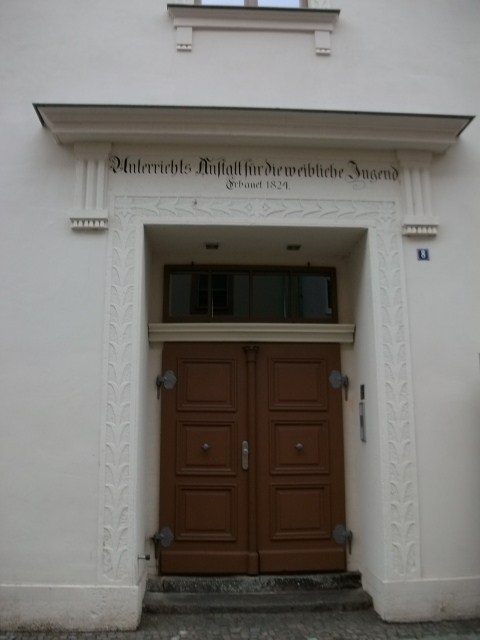
Vielleicht doch kein Faible der Engländer,
das Ungern-Koppeln bzw. -zusammenschreiben, Schnitzel?
Ehemalige Wittenberger Schulstätte.
Doch, hier ist es eben falsch ;-)
Aber in irgendeinem Thread wurde sich hier mehr oder weniger geeinigt, dass Eigennamen nicht unbedingt gekoppelt werden und sich nicht der gängigen Orthografie beugen müssen.
Vielleicht hätte ich meine mitschwingende Ironie
doch etwas LAUTER als nur faiblesque malen sollen, Schnitzel. ;-)
Wenn jemand so eigen ist, seinen Namen ungebunden lassen zu wollen,
obwohl er vielleicht gebunden ist, dann ist es ... seine Sache,
aber "Unterrichts Anstalt" — ein Eigenname?
Ich, jedenfalls, staune diese Türüberschrift
jedes Mal fassungslos (obwohl mit Türrahmen) an.
:-o
Edit: Obwohl das Gebäude ein wunderschönes ist und bleibt!
Ja, das dachte ich auch zuerst. Aber dann habe ich gelesen, daß die Jungs Maschinen restaurieren und dachte, daß der ganze Schrott vielleicht der Fundus ist, aus dem für die Restaurationen geschöpft wird.
Die Karte ist eine der ältesten und umfangreichsten Weltbilddarstellungen des Mittelalters. Fund- und wahrscheinlicher Herstellungsort: Kloster Ebstorf.
Auf der Karte wird das Rund der Erde dargestellt; sie ist so ausgerichtet, dass der Osten oben ist. Dort befindet sich auch die bildliche Darstellung des Paradieses. Im Zentrum der Karte liegt die heilige Stadt Jerusalem. Europa ist in der linken unteren Ecke dargestellt. Dort findet man Städte wie z.B. Lüneburg, Braunschweig, Meißen, Aachen, Köln, Kulmbach und Rom.Die Absicht des Autors war es nicht, eine geographisch korrekte Karte der Welt anzufertigen. Die Stadt Rom ist zum Beispiel fast genau so groß wie die Insel Sizilien. Vielmehr spiegelt die Karte das historische, mythologische und theologische Wissen dieser Zeit wider. Die Welt selbst wird mit dem Leib Christi verglichen, zu erkennen an Kopf, Händen und Füßen an den Rändern der Karte. Des Weiteren sind in der Karte das Paradies, die Arche Noah und der Turm zu Babel verzeichnet. Auf der Mythologie und antiken Sagen beruht beispielsweise die Darstellung der Amazonen.
Zur Karte
Über »Darstellung« lässt sich die Ansicht vergrößern, so dass man die Details in Schrift und Illustration bewundern kann. Viel Spaß! :-)
Nicht? Bei mir geht es ganz gut. Dauert ggf. ein paar Sekunden. Ich finde hier gerade auch die angebotenen Rollover-Übersetzungen interessant, welche es auf dem bloßen Bild (Link bertel) leider so nicht gibt.
:roll: Den hab’ ich Euch ja bereits hochgeladen. Aber leider wurde er von System runter skaliert. Daher zum Vergleich noch mal ein Screenshot mit dem Wikipedia-Bild (Fenstergröße wie eben). Dann seht Ihr den Unterschied. Muss aber dazu sagen, dass es bei der Flash-Darstellung »Beste Auflösung« nicht gestochen scharf abgebildet wird. Aber für mein Empfinden lohnt es sich trotzdem, da man das Schriftbild und Illustrationen besser erkennt und immer die Rollover-Bemerkungen dazu bekommt. Wie gesagt, es dauert eine Weile, bis das hochaufgelöste Bild nachgeladen wird. Da sollte man in der Zwischenzeit erstmal etwas anderes machen. (Finde ich aber bei so einer historisch-wissenschaftlichen Herangehensweise auch legitim.) :-)
Edit: Ich lad’ Euch gleich noch einen kleineren Ausschnitt der Flash-Darstellung »Beste Auflösung« hoch, dann sieht man es evtl. besser.
Hier ein Screenschnipsel unter Adam und Eva. Diese Ansicht ist natürlich immer noch »Nichts« gegen das Original von ca. 3,57 m Durchmesser auf 30 zusammengenähten Pergamentblättern. ;-)
Danke. Dann "funktioniert" die Flash-Karte doch, nur sind eben keine hochaufgelösten Daten unterlegt. Ich dachte, die "Details in Schrift und Illustration" wären sichtbar, sind sie aber nicht so wirklich ;-)
Im Vergleich zur Darstellung »Ganzes Bild« schon. Unter »hochaufgelösten Daten« verstehen wir natürlich etwas anderes. Aber selbst dort wird nur von »Beste Auflösung« gesprochen. Warum also Ihre Bemühungen schon wieder madig machen?
… Warum also Ihre Bemühungen schon wieder madig machen?
Ich mache nichts madig. Deine Aussage "so dass man die Details in Schrift und Illustration bewundern kann" hat einfach Erwartungen geweckt, die leider nicht erfüllt werden. Dabei ist das eine wirklich tolle Karte, die ich gern im Detail bewundert hätte :-)
... aber die Rollover-Flaggen helfen wirklich zur Orientierung, wenn man sich in der Welt nicht so auskennt :roll:
Ich finde die Karte hat etwas sehr ehrliches, nach dem Motto: »Ich sehe die Welt so, wie ich sie sehen will!«
Dass man die Texte nicht lesen kann, ist wirklich schade. Das könnte auch noch richtig interessant sein ...